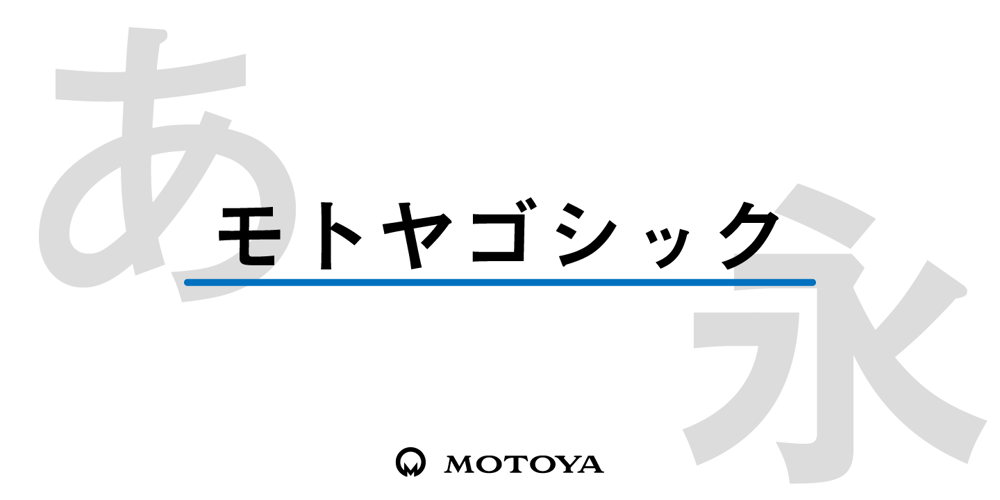
Motoya Gothic Font Family was designed by published by Motoya. Motoya Gothic contains 4 styles and family package options. ゴシック体は、明朝体のように横線や縦棒を装飾するウロコや、セリフといったものが無いので、骨格線そのものが命である書体です。また横線にも画数に応じた太さの調整が必要となるので、太さの統一性を持たせるのが非常に難しい書体とも言えます。モトヤのゴシック体ファミリーは、この二つの命題を克服すると同時に、背勢表現(縦棒や横線の両端につけるラッパ状のアクセント)を施すことにより、伝統と力強さと柔らかさを同時に感じさせる書体となっています。